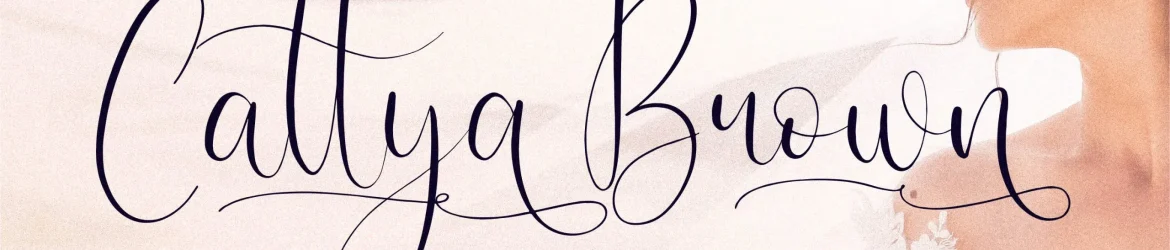
Cattya Brown Font – Download Grátis
A Cattya Brown Font é uma elegante tipografia romântica ideal para diversos tipos de projetos criativos. Seus traços finos e delicados dão vida a qualquer conceito visual, tornando-a perfeita para aplicar em sua identidade empresarial ou produto ao mesmo tempo que oferece um toque suave em designs pessoais, como selos de presente ou capas de livro. Ideal para projetos tanto profissionais quanto de lazer, esta fonte não só complementa e dá vida aos textos mais sofisticados, mas também se encaixa perfeitamente em designs pessoais. Desde a criação de uma identidade empresarial única até as etiquetas de sua próxima festa ou o design de selos exclusivos para seus amigos e familiares – seja qual seja o projeto, a Cattya Brown Font certamente fará um diferencial imenso. Além disso, ela é tão versátil que se adapta perfeitamente aos mais variados formatos de mídia, desde os famosos selos de presente até as etiquetas para suas compras e embalagens, proporcionando uma fidelidade perfeita em todos esses contextos. Seja o momento de sua vida que você esteja criando: seja uma lembrança especial ou um design profissional impecável, a Cattya Brown Font pode ajudá-lo a dar a seus projetos aquele toque único e incrivelmente bonito.